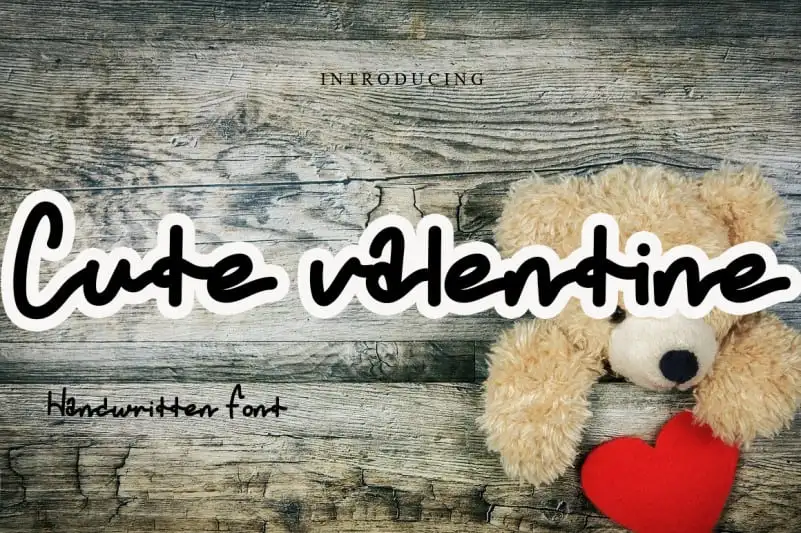
Cute Valentine Script Font – Download Grátis
A ‘Cute Valentine Script Font’ é uma fonte handwritten única e interessante, com seu estilo irregular e emotivo, perfeita para aqueles projetos que exigem criatividade e personalização. Suas linhas elegantes e nuances de traço tornam essa fonte uma peça indispensável para qualquer biblioteca de fontes. Ela traz vida a qualquer design que seja impresso com ela, tornando os textos não apenas legíveis, mas também irresistivelmente encantadores. Seja você criando cartões de aniversário em tempos de feriados amorosos ou desenvolvendo material digital para sua empresa, essa fonte será um complemento incrível a qualquer projeto. A designer levincreative criou uma fonte que vai além da simples elegância estética: ela oferece um toque único e divertido que pode transformar os elementos mais comuns em algo memorável. Com seu conteúdo vibrante e sua forma não-linear, ‘Cute Valentine Script Font’ é a escolha perfeita para aqueles que querem adicionar um toque delicado e nostálgico aos seus trabalhos. Não espere, descubra o encanto da ‘Cute Valentine Script Font’.